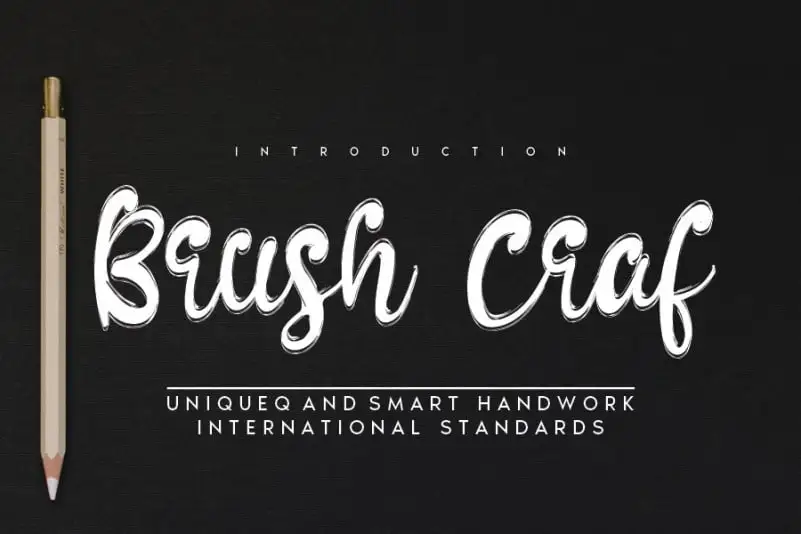
Brush Craf Script Font – Fonte Grátis
Brush Craf Script Font
Brush Craf Script Font é uma fonte única criada através de um canivete-pen, oferecendo uma experiência visual que vai além dos limites comum das serifas digitais. Suavemente curvada e personalizada, ela se encaixa perfeitamente em um vasto espectro de projetos de design, desde marcas sofisticadas até assinaturas elegantes, e tudo por meio de logotipos, etiquetas, convites de casamento e muito mais. A sua aparência cuidadosamente elaborada faz dela uma escolha ótima para qualquer projeto onde um toque delicado e autêntico seja valorizado. Não importa o tamanho do seu trabalho ou a finalidade dos designes, Brush Craf Script Font está aqui para enriquecer cada detalhe, garantindo que sua mensagem tenha força ao ser transmitida através da aparência textual.